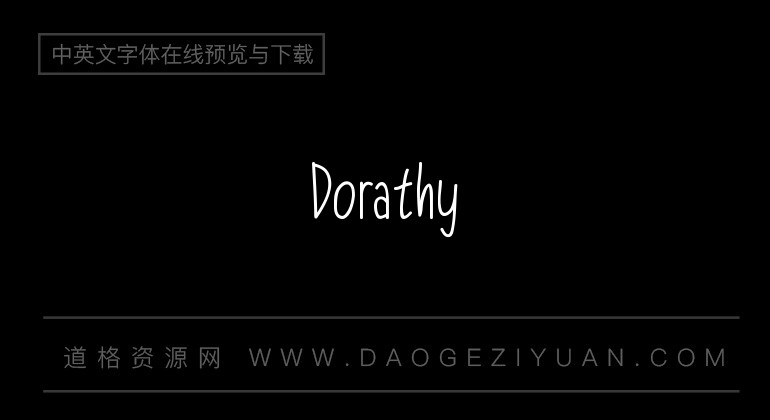
Dorathy
Dorathy字体是一种平滑、现代而又充满活力的楷体字体,它有着良好的可读性和可视性,很容易让人们记住它。它的字体设计简洁大方,具有流畅的轮廓和清晰的字形,能够提升文字的可读性和可视性,使文字更加易读、易懂。它也具有良好的空间感,可以完美地显示出文字的结构和情感,为文字提供更多的艺术表现力。
Dorathy是一款非常不错的手写艺术字体,具有很好的视觉感,适合于文化类的宣传设计、商业类品牌的广告和产品包装设计以及个性化文字排版等较多场景。